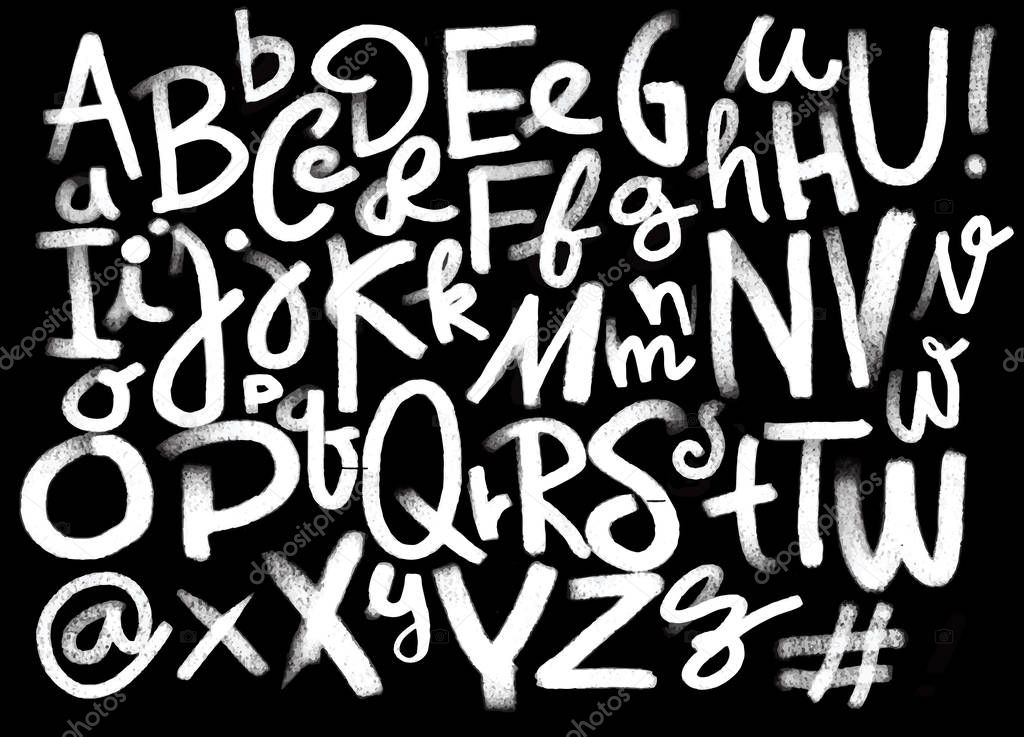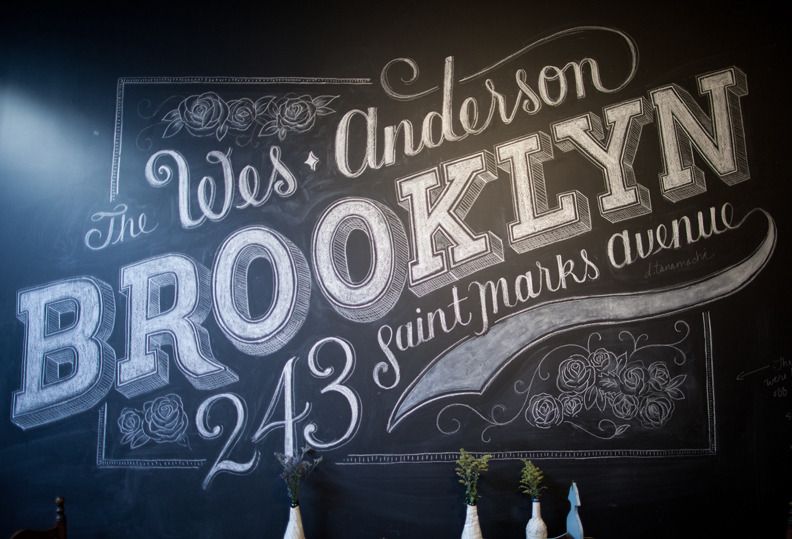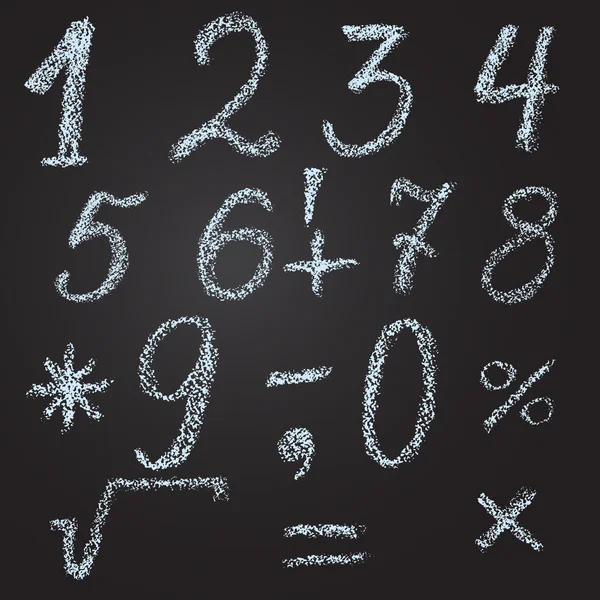
Современные шрифты по мотивам русских. Лучшие бесплатные шрифты для дизайнеров
Типографика это искусство, в котором органично сочетаются техника, изобретательность и расчет на перспективу. За редким исключением хороший дизайн подразумевает хорошую типографику. Неважно, над чем работает дизайнер: проектирует сайт или пользовательский интерфейс, работает над макетом брошюры или создает логотип для бренда – везде одним из ключевых элементов успешного проекта будет шрифт. При этом огромное значение имеет не только выбор шрифтов, но и их соответствие друг другу, а также цветовые решения. Вариантов может быть очень много, но от правильного выбора шрифта во многом зависит, будет успешным проект или его ждет провал. Порой достаточно упустить из виду даже второстепенные детали, чтобы свести на нет все творческие усилия, которые были направлены на создание выдающегося дизайна. К счастью, есть множество ресурсов, которые помогут в работе с типографикой.
Многим дизайнерам, особенно новичкам, свойственно стремление ко всему новому.
- Дизайнер: Альберт-Жан Пул
- Дата выхода: 1995
- Издатель: FontFont
Шрифт FF DIN был создан голландским дизайнером Альбертом-Жаном Пулом. Первый вариант был представлен в 1995 году, затем разработка продолжилось и к моменту завершения работы в 209 году, семейство FF DIN включало в себя 20 начертаний. Шрифт отлично подходит для редакционного и издательского дела, а также может использоваться в рекламе и дизайне упаковки, в брендинге и других сферах творчества, таких, как дизайн плакатов и биллбордов. Хорошо выглядит FF DIN и на экране компьютера, так что его можно задействовать в веб-дизайне. У FF DIN имеется ограниченная поддержка кириллицы, что немаловажно для российских дизайнеров.
- Дизайнер: Ханнес фон Доррен
- Дата выхода: 2010
- Издатель: HVD Fonts
Brandon Grotesque – это очень известный шрифт без засечек, состоящий из шести наборов с различной толщиной штриха и шести соответствующих основным курсивов. В основе шрифта лежат геометрические формы, оптически скорректированные для лучшей читаемости символов. Brandon Grotesque по праву считается функциональным и элегантным шрифтом. Начертания Light и Bold хорошо смотрятся на лайтбоксах или витринах, а Regular и начертания средней толщины подойдут для набора длинных текстов. Данный шрифт является отличным выбором для работы над проектами, где требуется типографика профессионального уровня. Brandon имеет расширенный набор символов для поддержки языков Центральной и Восточной Европы, но кириллицы нет, несмотря на то, что в списке языков русский присутствует.
- Дизайнеры: Сол Гесс, Моррис Фуллер Бентон
- Даты выхода: 1990-1995-2007
- Издатель: Monotype
Знаменитый шрифт Century Gothic во многом напоминает Futura, однако это уникальный шрифт, который является производным двух отдельных шрифтов ITC Avant Garde и Twentieth Century – основных конкурентов Futura.
Century Gothic – это легкий, воздушный шрифт с чистыми и резкими окончаниями штрихов и очень хорошо проработанным курсивом. Данный шрифт идеально подходит для заголовков или для набора крупными символами.
- Дизайнер: Марк Симонсон
- Дата выхода: 2005
- Издатель: Марк Симонсон
Семейство Proxima Nova представляет собой реконструкцию известнейшего шрифта Proxima Sans. Набор Proxima Nova был расширен до 48 полнофункциональных шрифтов Open Type. Новая Proxima состоит из трех больших групп, в каждой из которых по 16 шрифтов с различной толщиной штриха. Стилистически данный шрифт является сбалансированным сочетанием гуманистических пропорций и геометрического подхода к проектированию. Кириллица есть.
- Дизайнер: Адриан Фрутигер
- Дата выхода: 1998
- Издатель: Linotype
Шрифт Avenir также содержит отсылки к Futura, но в нем нет такой радикальной геометрии, как у его предка. У Avenir вертикальные штрихи толще, чем горизонтали и укороченные восходящие штрихи.
- Дизайнеры: Эдуард Хоффман, Макс Мидингер
- Дата выхода: 1983
- Издатель: Linotype
Helvetica является одним из самых популярных шрифтов в истории мировой типографики, этот шрифт оказал огромное влияние как на рекламу, так и на маркетинг. Семейство состоит из 51 начертания с различной толщиной штриха, разной шириной и курсивом. Это классический шрифт без засечек, нейтральный и неподвластный времени. Helvetica Neue является наиболее безопасным выбором практически для всех видов дизайна.
- Дизайнеры: Адриан Фрутигер, Акира Кобаяши
- Дата выхода: 2004 (разработка продолжается)
- Издатель Linotype
В то время как основной набор Avenir является одним из самых больших шрифтовых семейств, созданных для того, чтобы решить некоторые проблемы с отображением на экране компьютера, побочный проект Next Pro, созданный студией Linotype, направлен прежде всего на эстетику.
Полный набор Avenir Next Pro состоит из 32 шрифтов: 8 начертаний с разной шириной штриха (каждый с версией Roman и Italic), а также шрифтов с различной шириной символов – Normal и Condensed. Глиф был расширен за счет включения малого капса, верхних и нижних индексов и лигатур.
- Дизайнер: Энрике Эрнандес
- Дата выхода: 2016
- Издатель: Latinotype
Isidora представляет собой современный геометрический шрифт с упором на функциональность. Несмотря на то, что Isidora очень выразительный и дружелюбный шрифт – это в своем роде манифест рациональности. Семейство состоит из 28 шрифтов с двумя подсемействами, так что найти начертание с подходящей толщиной штриха не составит проблемы. Шрифт идеально подходит для брендинга, логотипов, заголовков, его можно использовать в веб-дизайне, дизайне упаковки и в полиграфии. К сожалению, кириллицы нет, однако шрифт определенно заслуживает внимания, он очень стильный, с симпатичными закруглениями, которые делают его не таким строгим.
- Дизайнер: Рене Бидер
- Дата выхода: 2016
- Издатель: Рене Бидер
слой примерно до 65% и сотрите некоторые фрагменты, чтобы он выглядел как
ластик снял часть. Теперь это должно выглядеть как на картинке выше «Шаг
8-дюймовый текст.
Шаг 9:
Теперь пора покончить с этим. Найдите свой инструмент кисти и измените кисть
на что-то мягкое вроде 27 и цвет на черный. Теперь кисть слева
верхний и нижний углы, чтобы получить эффект тени. Затем добавьте более мелкие
в правом верхнем и нижнем углах. Теперь у вас должно быть что-то вроде
изображение над текстом «Шаг 9».